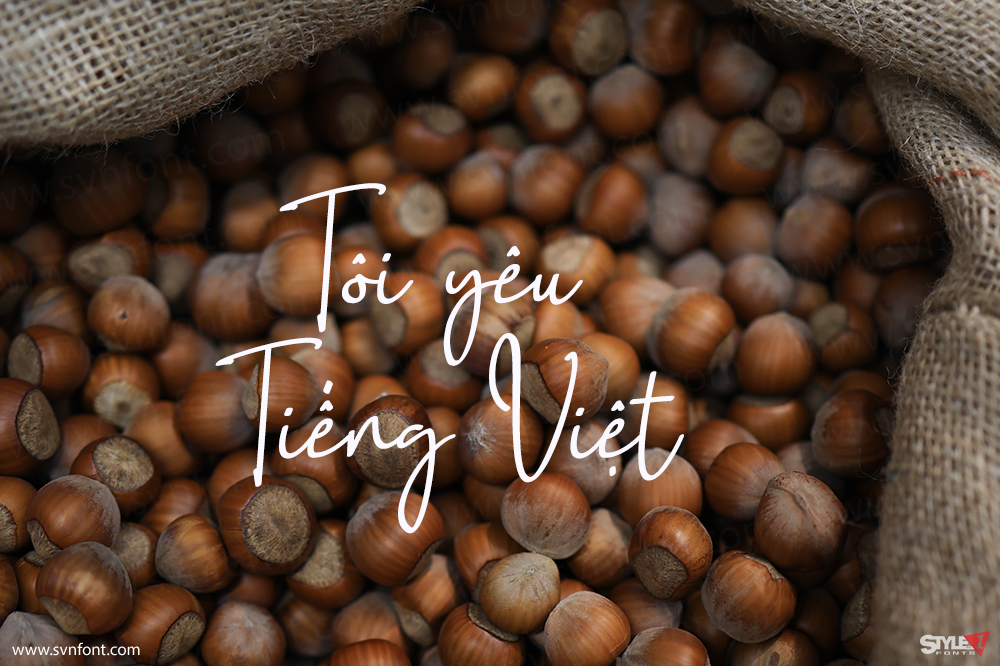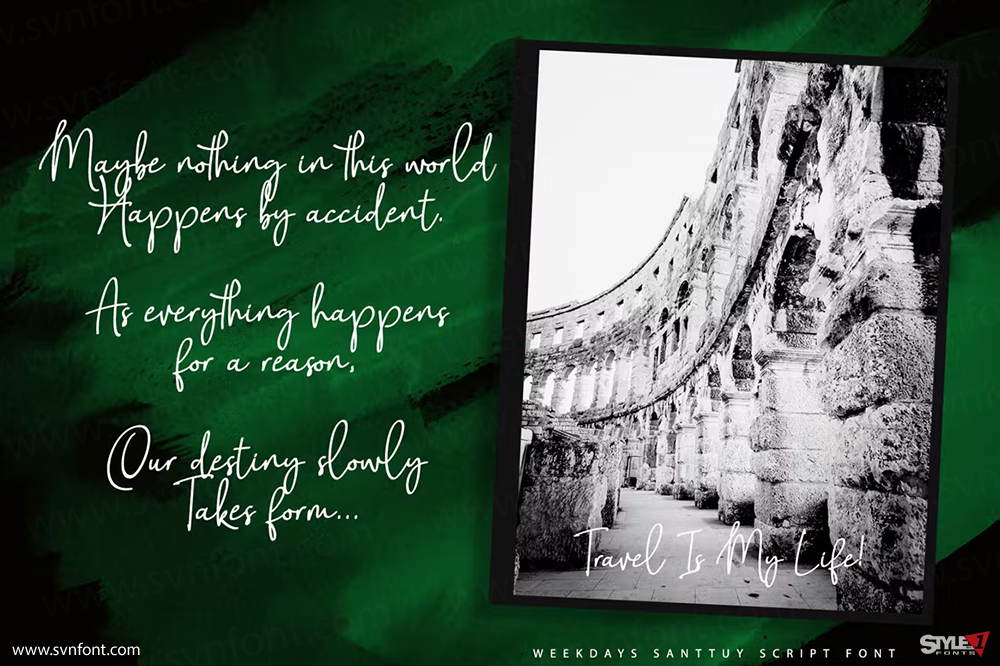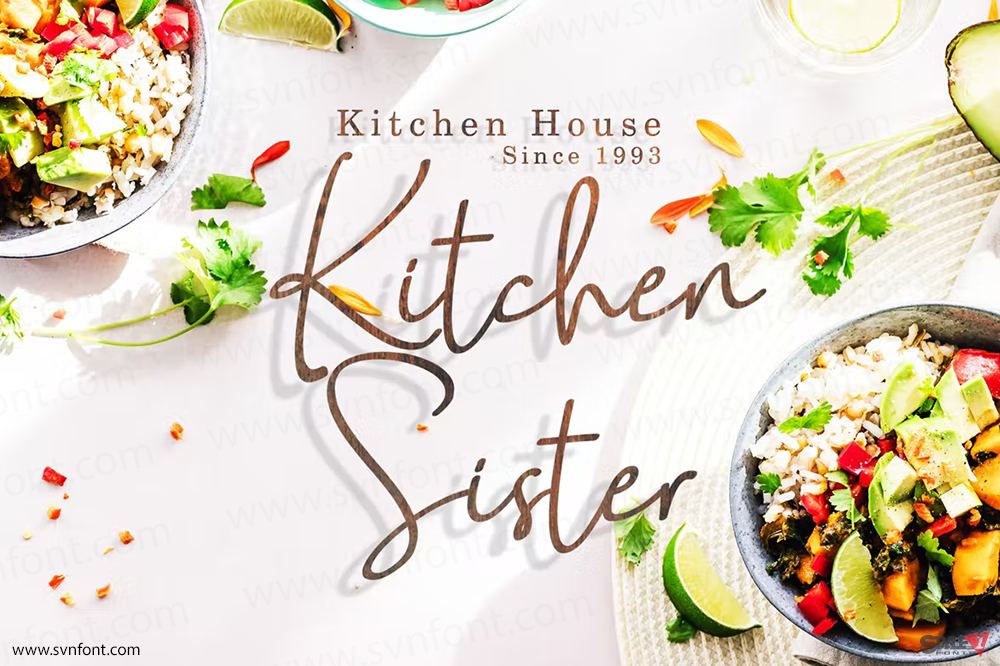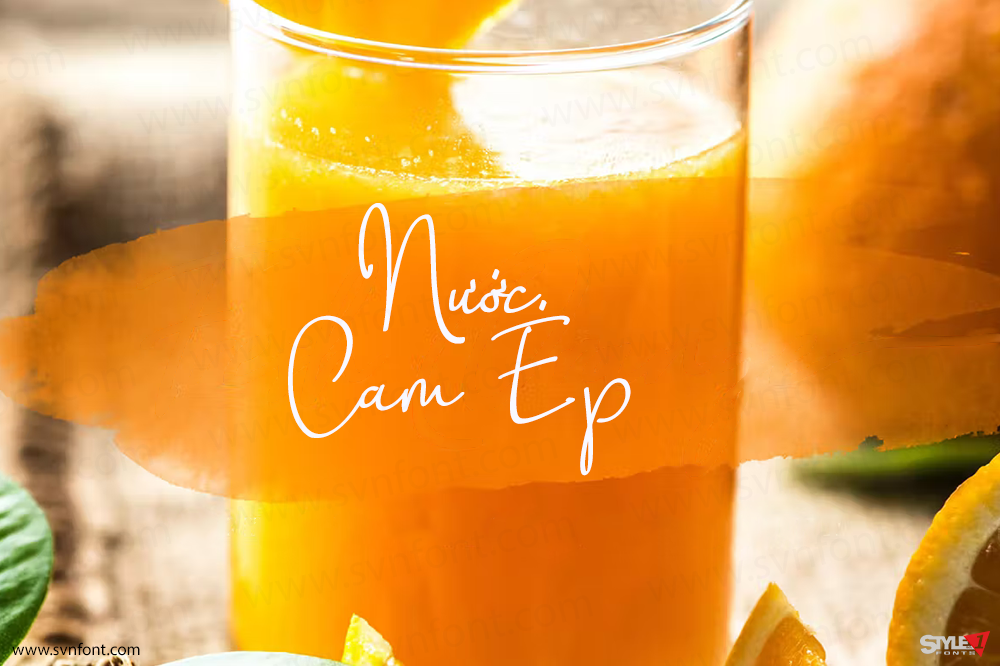
Weekdays Santtuy là một font tuyệt vời cho bất kỳ dự án nào của bạn! Font chữ này được tạo ra với phong cách tuyệt vời và đẳng cấp, đi kèm với cảm giác tự nhiên, rất nhiều nét nối (ligatures) & ký tự thay thế (alternates). Chúng tôi giữ cho font chữ này trông sang trọng, dễ đọc, thanh lịch, sành điệu, bắt mắt và hoàn toàn dễ sử dụng.
Weekdays Santtuy là lựa chọn tuyệt vời cho hình mờ trên các sản phẩm thương hiệu, thiết kế, đám cưới, nhiếp ảnh, chữ ký, thiết kế logo, bìa album, danh thiếp, trích dẫn và nhiều dự án thiết kế khác.